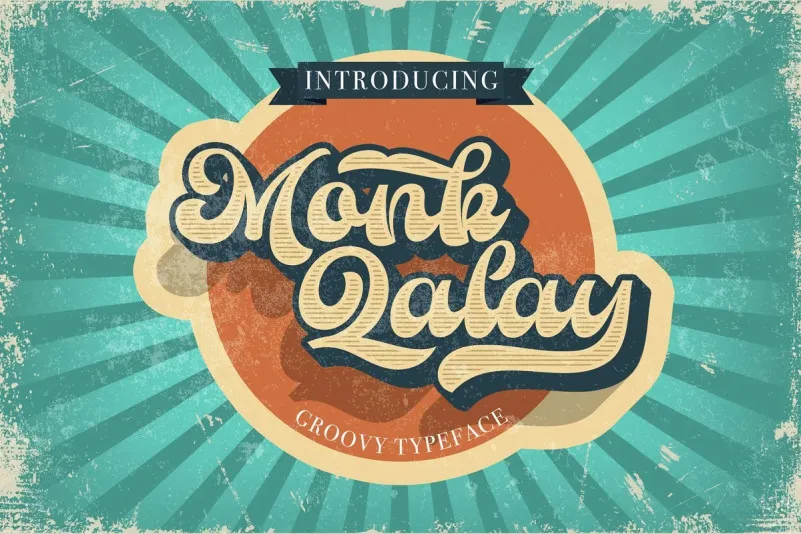
Através do Monk Qalay Font, você encontrará uma opção para adicionar um toque único e engraçado a qualquer projeto criativo. Inspirada nos designs e ilustrações dos anos 70, esta font foi meticulosamente criada por designers talentosos da 99designs, com um estilo divertido, colorido e clássico que não é sério, mas é rico em beleza e individualidade. Com sua facilidade de memorização, a Monk Qalay Font se torna uma representação perfeita do seu design. Perfeito para aqueles que buscam algo diferente na lista de fontes disponíveis hoje, esta elegante escolha oferece um toque único ao seu projeto gráfico ou tipográfico. Sem dúvida, é o tipo de fonte ideal para quem busca uma sensação de nostalgia e criatividade contemporânea em cada letra impressa.